Audi-მ, საზოგადოებას, განახლებული დიზაინ სტილი წარუდგინა, სადაც მნიშვნელოვანი ნაწილი ეთმობა Variable fonts-ს (ცვალებად ფონტებს), იგივე flexible typography-ს. ანუ ამ ცვლილებით, ბრენდს, ყველა განსხვავებულ შემთხვევაზე, ისე შეუძლია დიზაინის მორგება, რომ მაქსიმალურად აღქმადი იქნება.
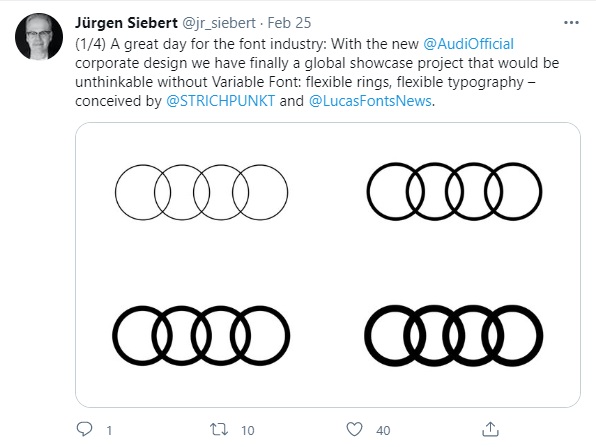
„ეს flexibility ეხება ლოგოსაც, რომელიც შტრიხის სისქის მიხედვით, სხვადასხვა სიტუაციაში, შეიძლება, შეიცვალოს. თუმცა, ფორმების კუთხით, ახალი რამ ნაკლებადაა. პირიქით, როცა ცდილობენ ბრენდის ვიზუალური ნაწილის განახლებას, თანამედროვე ტენდენციების მიხედვით, მიდიან კიდევ უფრო უკან წარსულში და იქიდან იღებენ კარგ მაგალითებს“, – გვითხრა კომუნიკაციის დიზაინერმა აკაკი რაზმაძემ, როცა ამ სიახლის შეფასება ვთხოვეთ.
კიდევ უფრო რომ გავამარტივოთ საქმე, იმ შესაძლებლობებზეც გეტყვით, რასაც ბრენდებს Variable ფონტები და ლოგოები აძლევს.
„ასეთ დროს შესაძლებელია შრიფტის წონები (შტრიხის სისქის მიხედვით განსხვავება) ვცვალოთ მარტივად და იმის მიხედვით დავაყენოთ, თუ რა საჭიროების წინაშე ვართ. მაგალითად, მანქანის მონიტორზე შედარებით სქელი შტრიხები გვხვდება, რომ მარტივი აღსაქმელი იყოს მძღოლისთვის. პოსტერებზე, სადაც დიდი ზომის სათაურებია, შესაძლებელია Ultra Light ან Bold წონების გამოყენებაც, ესეც ხასიათის მიხედვით. დიზაინერი არჩევანს აკეთებს, როგორც სტილის ისე პრაქტიკულობის გათვალისწინებით. შესაბამისად, შესაძლებლობები უსაზღვროა ამ დროს. იგივე ეხება ლოგოსაც, როცა ლოგოც შრიფტის მსგავსად Variable არის“, – ამბობს აკაკი რაზმაძე.
Audi-ს განახლებული დიზაინ სტილი გერმანელმა ტიპოგრაფმა და დიზაინერმა ერიკ შპიკერმანმაც შეაფასა. აღნიშნა, რომ რეალურად, ეს 1990-იანებში, „აუდისთვის“ მის სტუდიაში შექმნილი ნამუშევრების კარგი განახლებაა.
თუმცა, ეს ყველაფერი არ არის. Audi-მ ბრენდის „გაიდლაინებიც“ გამოაქვეყნა, სადაც თითოეული პუნქტი დეტალურადაა აღწერილი და განმარტებული.
„ეს ახალი სტანდარტია.ზოგიერთი ბრენდი თავის „გაიდლაინებს“ არ აქვეყნებს და ეს ცოტა, გაუგებარია. აქ ძალიან კარგად არის აღწერილი ყველა დეტალი, თემების მიხედვით არის განხილული. თუ ამ „გაიდლაინს“ ვნახავთ, აღმოვაჩენთ, რომ რეალურად ყველაფერზე აქვს ბრენდს ნაფიქრი, ფაქტობრივად რებრენდინგია, დიზაინით დაწყებული კომუნიკაციით დამთავრებული ყველაფერი განახლებულია“, – ამბობს აკაკი რაზმაძე.